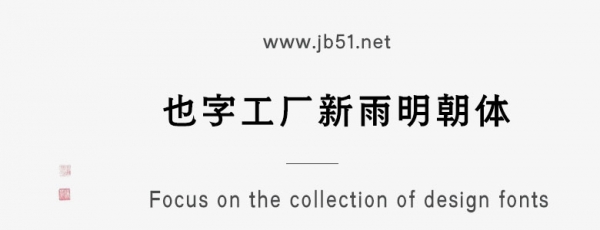
也字工廠新雨明朝體是由也字工廠出品的藝術(shù)字體 ,字體筆觸適中,字形端正,具有很好的視覺(jué)感,適合應(yīng)用于藝術(shù)設(shè)計(jì)、平面宣傳設(shè)計(jì)、網(wǎng)頁(yè)設(shè)計(jì),書(shū)法字帖等領(lǐng)域。有需要的朋友快來(lái)本站下載使用吧。